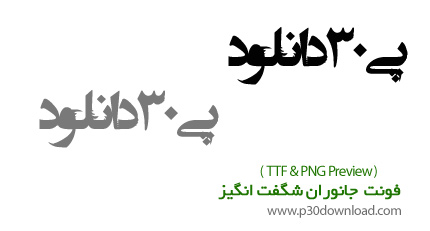
دانلود فونت فارسی و انگلیسی جانوران شگفت انگیز Fantastic Beasts Font
فونت جانوران شگفت انگیز را آقای محمدرضا جوادی طراحی کردند. این فونت ادیتی است زیبا از فونت انتظار ظهور. این فونت جزو فونتهای دکوراتیو (تزئینی دسته بندی می شود.